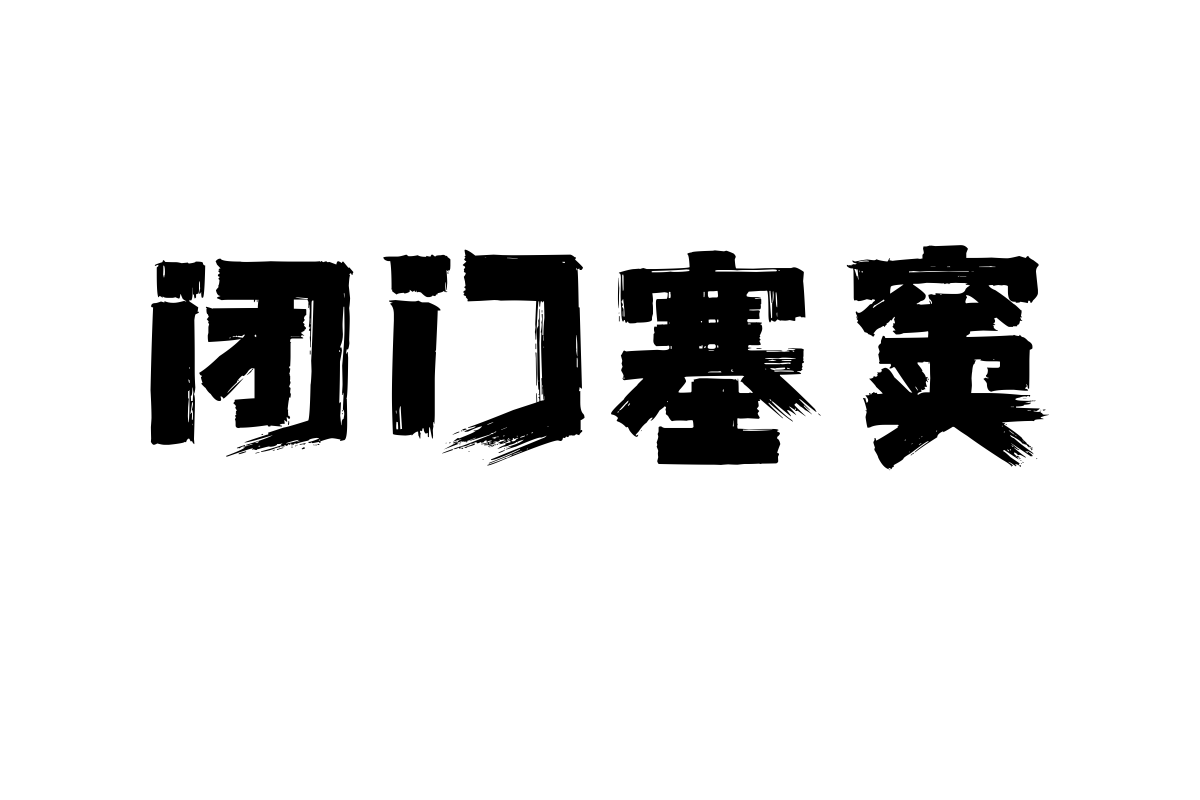
上首方义手刷体是一款专为手写笔记设计的字体。它的设计灵感来源于传统的书法艺术,旨在为用户提供一种更加接近手写体验的书写感受。该字体具有以下特点:
1. 笔触流畅:上首方义手刷体的笔画线条流畅自然,仿佛是真实的手指在纸上滑动,给人一种轻松愉快的书写体验。
2. 字形规整:该字体的字形结构规整,每个字都呈现出一种独特的美感,使得书写过程更加顺畅。
3. 可读性强:上首方义手刷体注重易读性,字形大小适中,间距均匀,方便用户快速识别和阅读。
4. 适合手写:该字体特别适合手写笔记,其笔触流畅的特点使得书写过程更加轻松愉快。同时,它也能适应印刷需求,保持文字的清晰度和可读性。
总之,上首方义手刷体是一款非常适合手写笔记的字体,它能够为用户带来更加舒适、自然的书写体验。